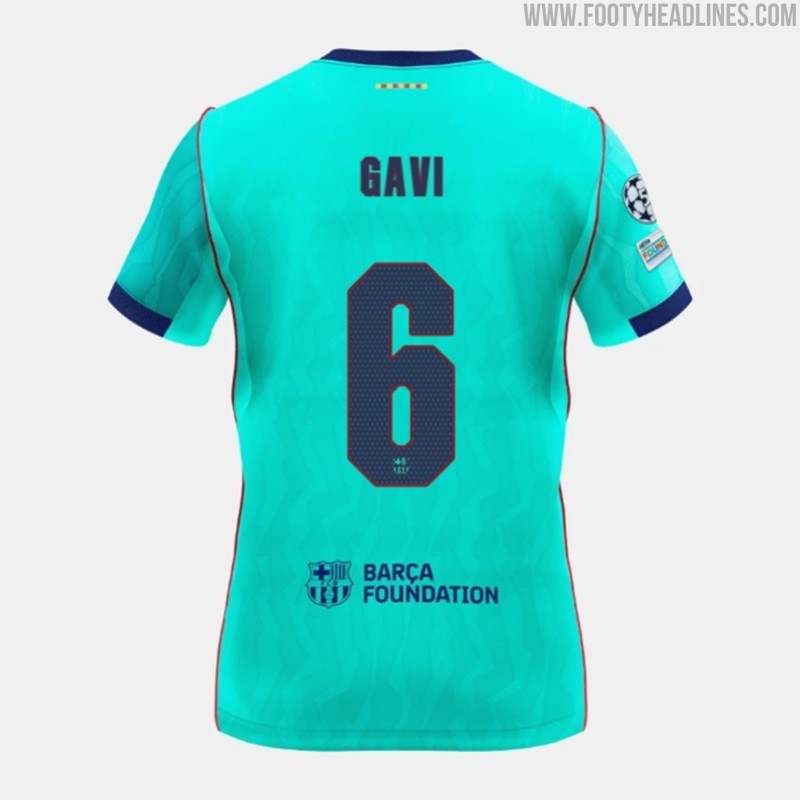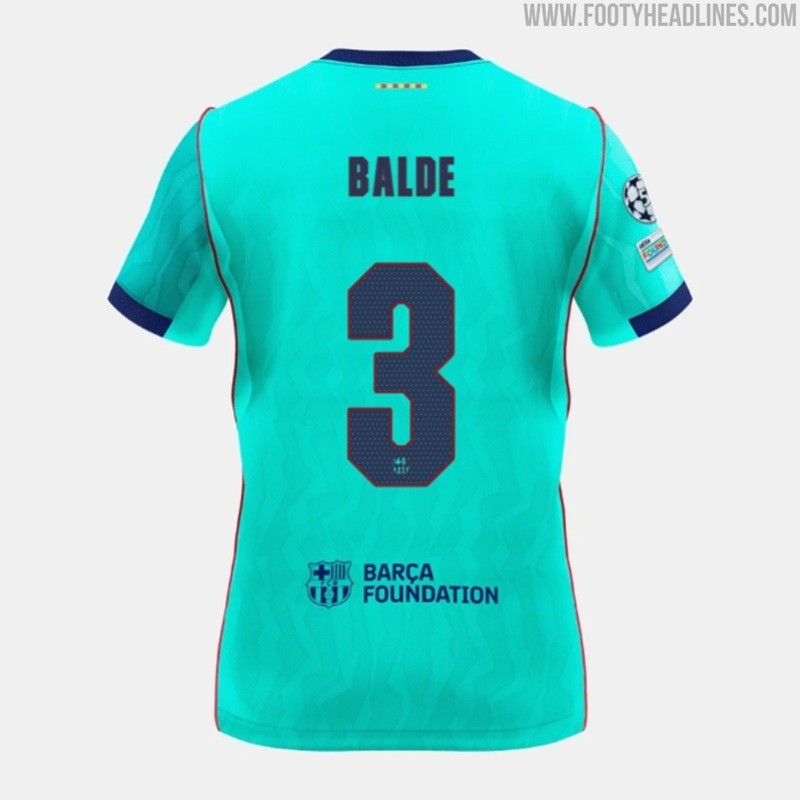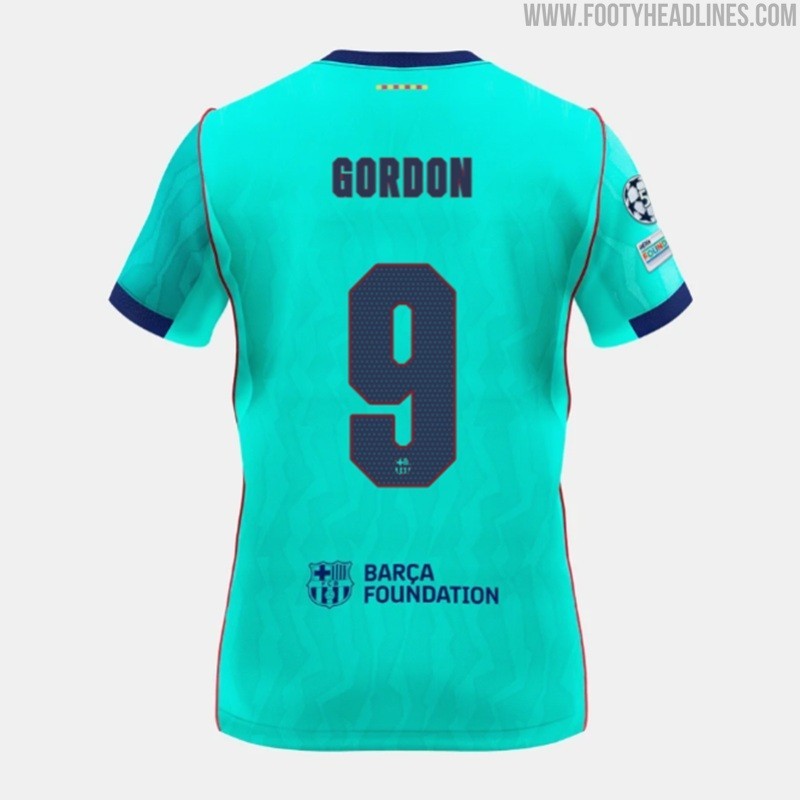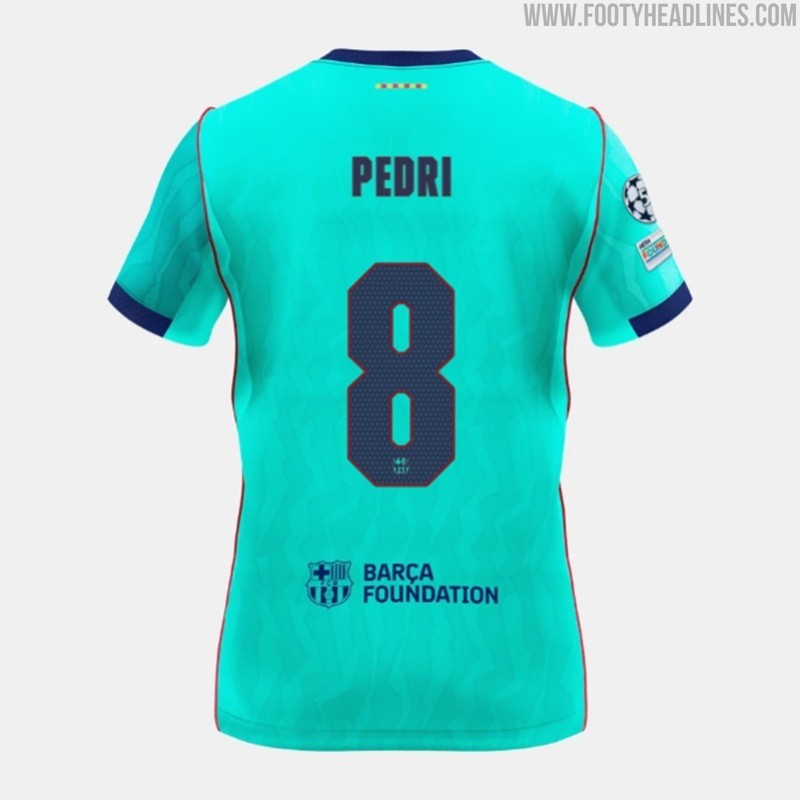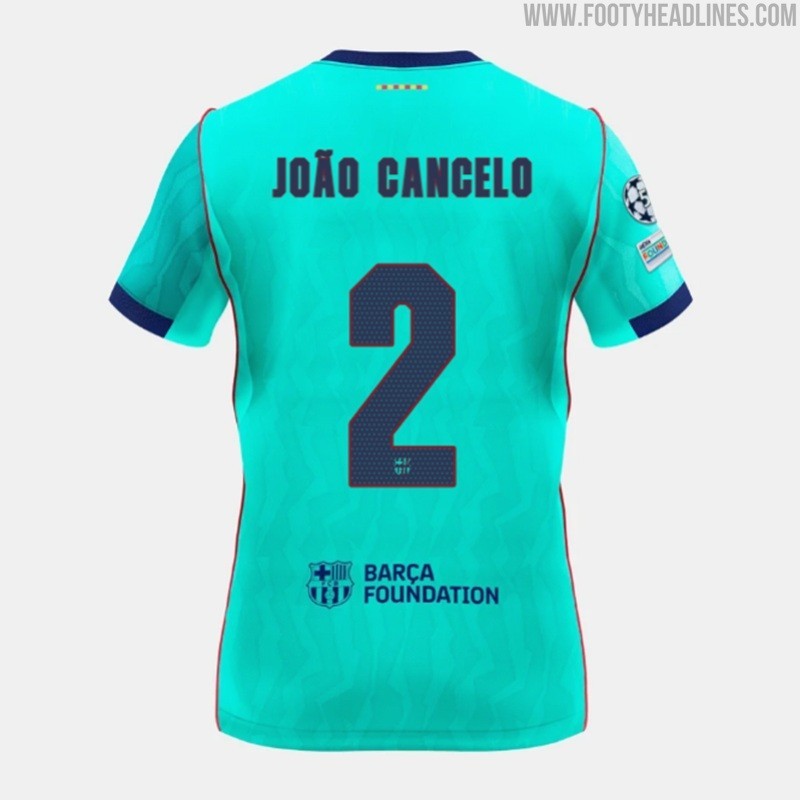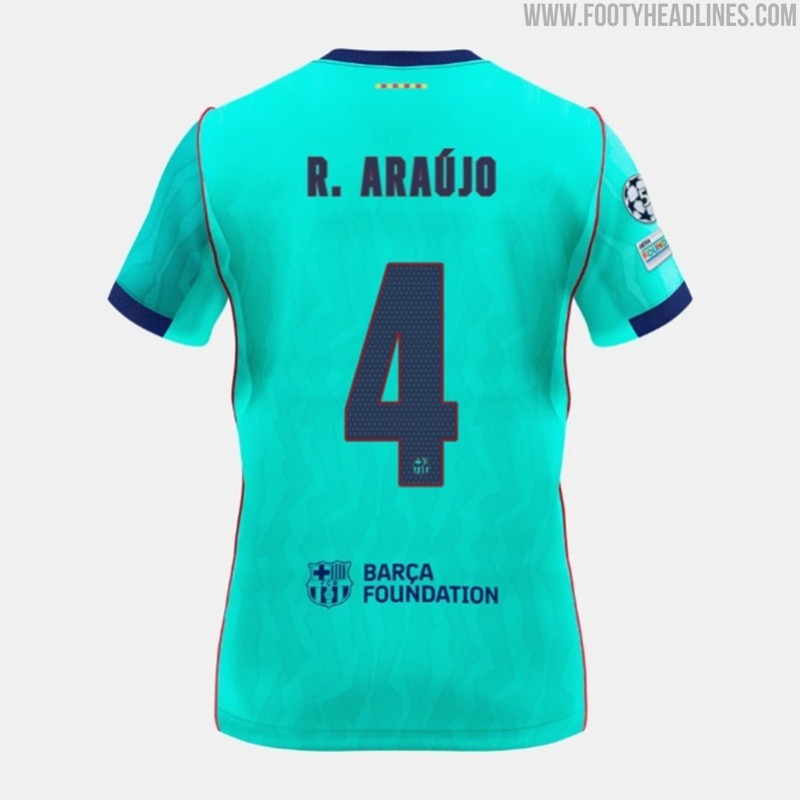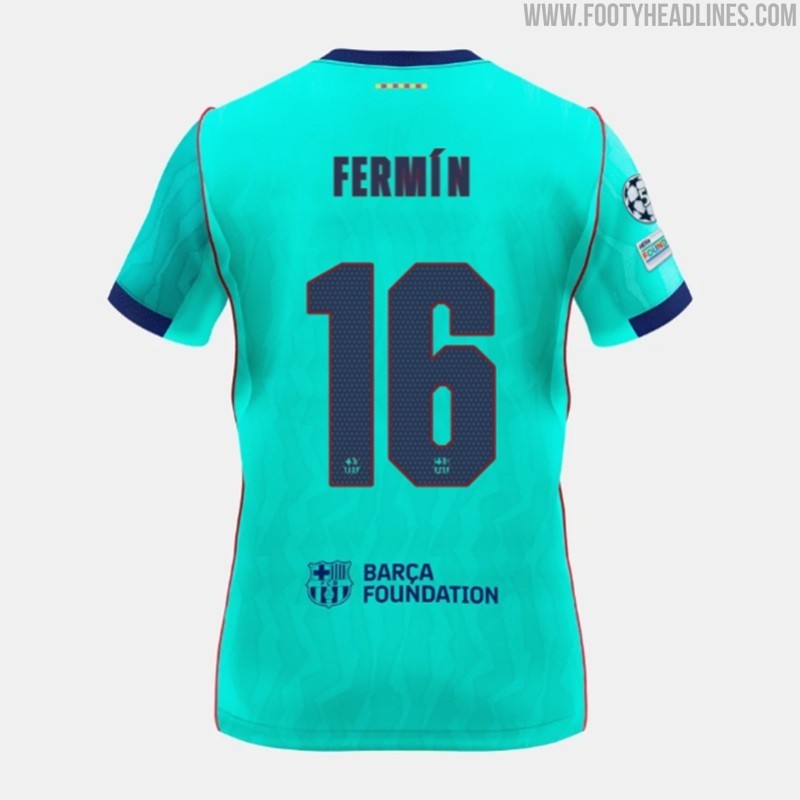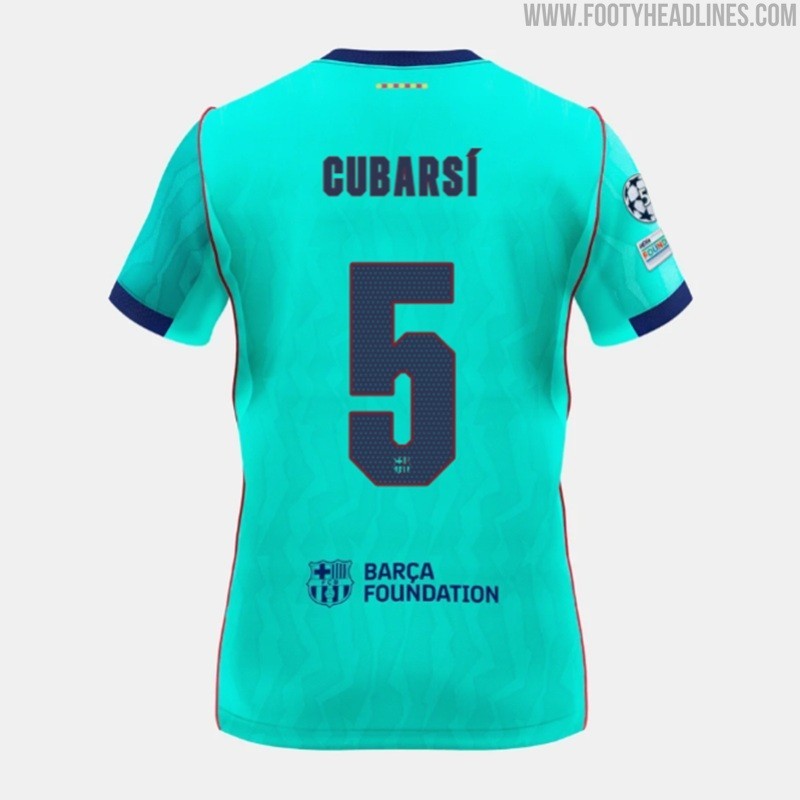
Völlig neue Schriftart für das dritte Trikot des FC Barcelona 26–27 veröffentlicht
• Neue Schriftart des dritten Trikots: Der FC Barcelona hat eine brandneue, maßgeschneiderte Schriftart exklusiv für sein drittes Trikot der Saison 2026–2027 vorgestellt.
• Designmerkmale der Schriftart: Die neue Schriftart zeichnet sich durch eine moderne, strukturierte, eckige und blockartige Ästhetik aus, die sich von den weicheren Heim- und Auswärtstrikot-Schriftarten unterscheidet und für optimale Sichtbarkeit dunkelblau ist.
Nach der offiziellen Vorstellung ihres neuen dritten Trikots hat der FC Barcelona eine brandneue, maßgeschneiderte Schriftart vorgestellt, die exklusiv für das dritte Trikot der Saison 2026–2027 entworfen wurde.
Schriftart des FC Barcelona-Dritten Trikots 26–27
Schau dir unten die neue Schriftart des FC Barcelona-Dritten Trikots 26–27 an.
Die neue Schriftart für das dritte Trikot 26–27 des FC Barcelona zeichnet sich durch eine ausgesprochen moderne, strukturierte Ästhetik aus, die sie vom Rest der Vereinskollektion 2026–2027 abhebt.
Im Gegensatz zu der weicheren, runderen und stilisierten Schriftart auf den Heim- und Auswärtstrikots von Barcelona für die Saison 2026–2027 besticht die Schrift des dritten Trikots durch ein deutlich eckigeres, blockartigeres und kantigeres Design. Die scharfen Kanten und kantigen Proportionen verleihen den Spielernamen und Rückennummern auf dem Rücken des leuchtend türkisfarbenen Trikots ein klares, Hightech-mäßiges Aussehen.
Die in dunklem Marineblau gehaltenen Zahlen und Buchstaben bilden einen maximalen Kontrast zur leuchtenden Grundfarbe und sorgen so für optimale Sichtbarkeit auf dem Spielfeld.
FC Barcelona 26–27 Schriftarten